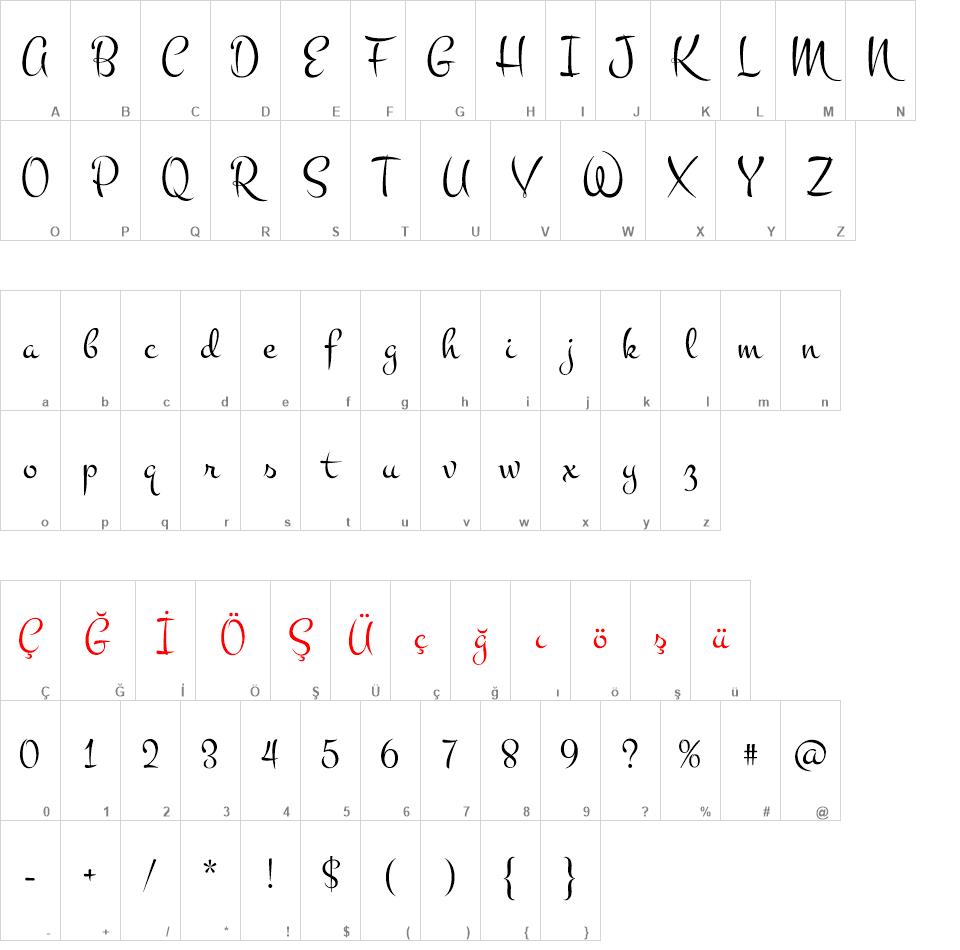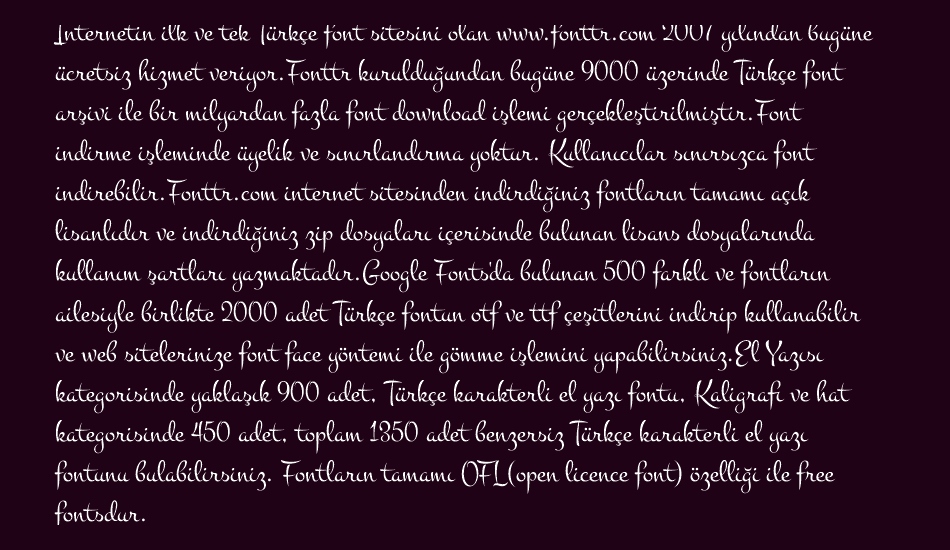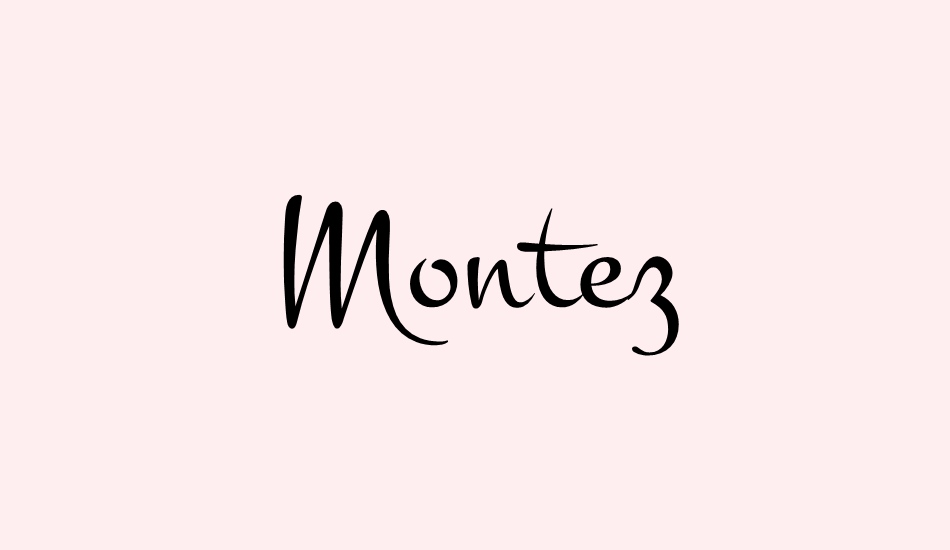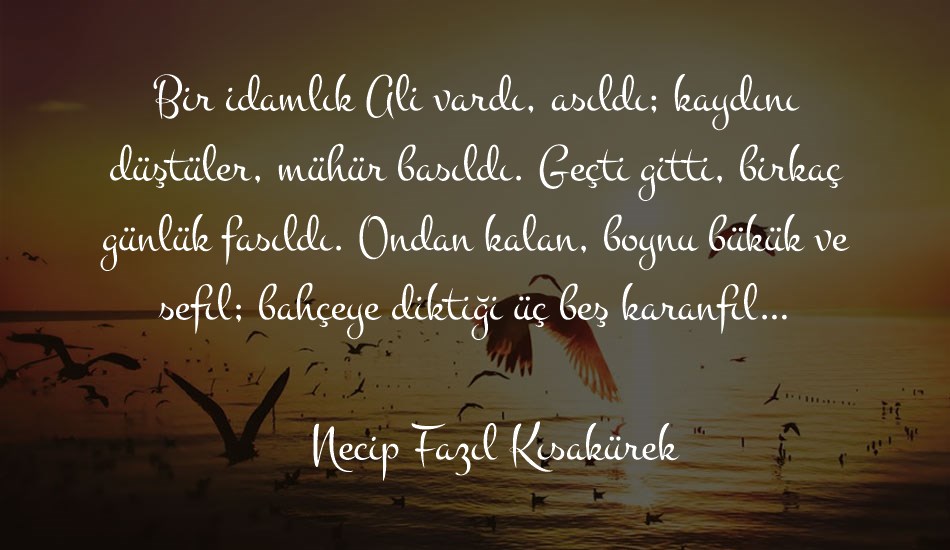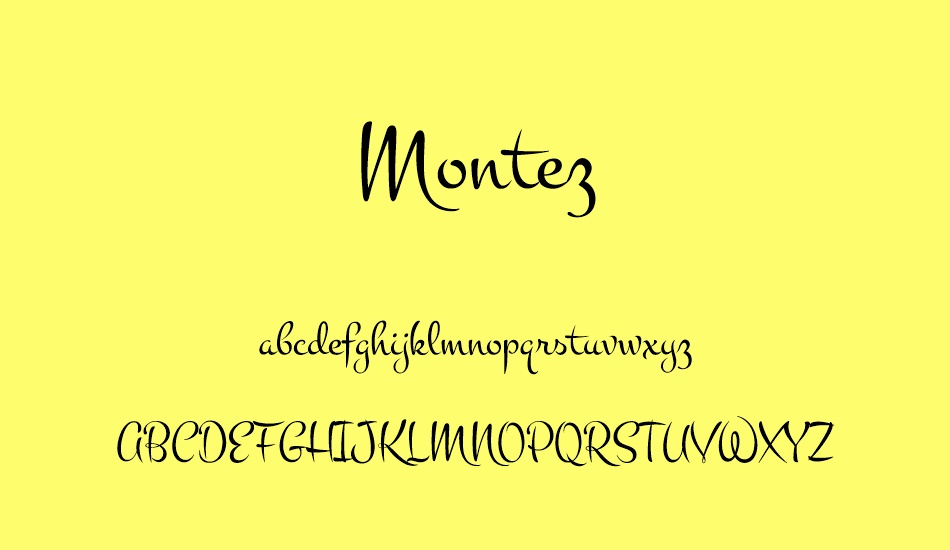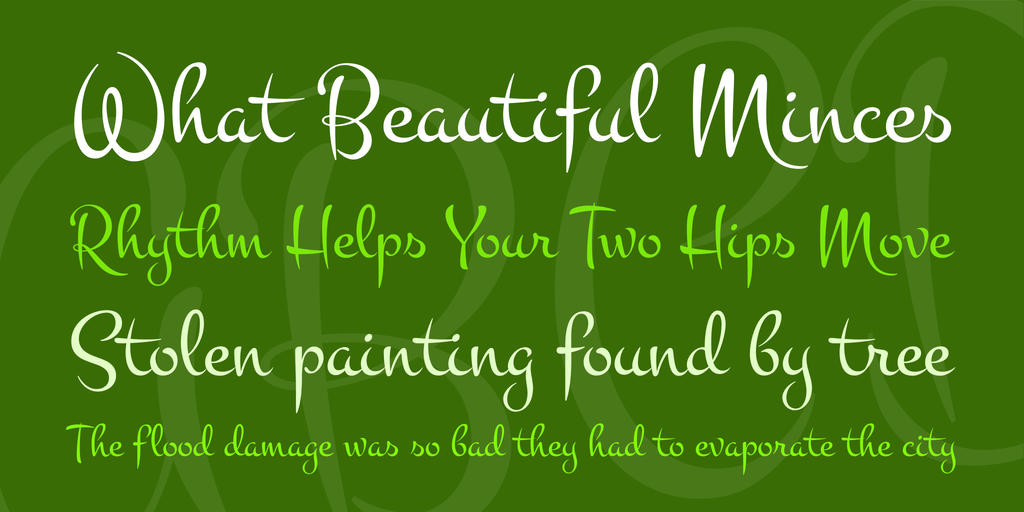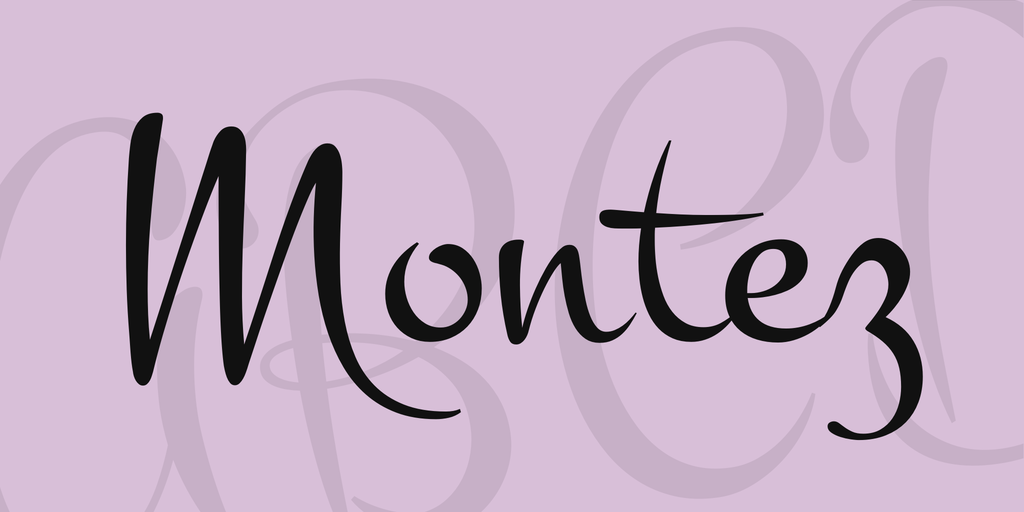
Montez Font font
Montezuma, 1960'lı yıllara ait güzel ürün reklamlarından esin kaynağı olan bir yazı tipi fontudur. Süpürme darbeleri, küçük bir drama, "joie de vivre" ya da Yaşamın Sevinci özelliğini gerektiren görüntü kullanımları için ideal bir zevk ve zerafet hissi kazandırıyor. En iyi okunabilirlik için en iyi ayarlar orta ve büyük metin boyutlarıdır.